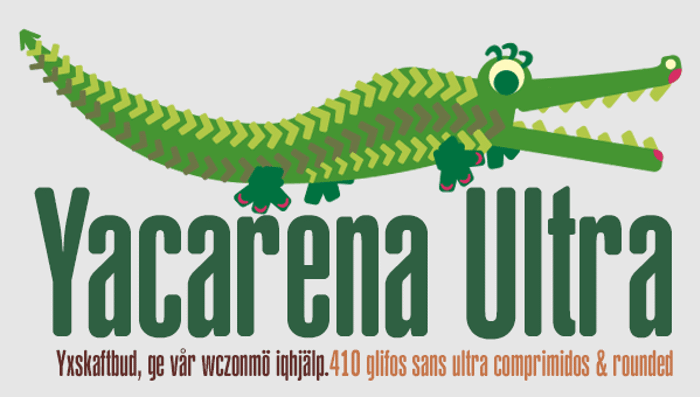
Yacarena Ultra FFP Font
Yacarena Ultra es un proyecto tipográfico surgido de mi necesidad redundante de disponer de una fuente muy condensada para ciertos trabajos de diseño gráfico donde la cantidad de texto en grandes títulos complican la composición.
Yacarena Ultra is a typographic project emerged from my redundant to have a very condensed font for some graphic design work where the amount of text in large titles need complicated composition.